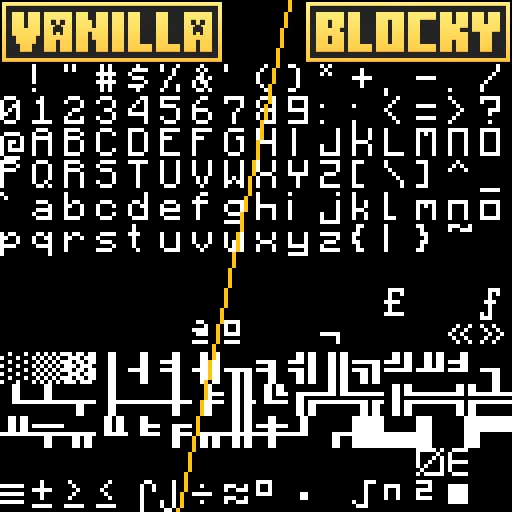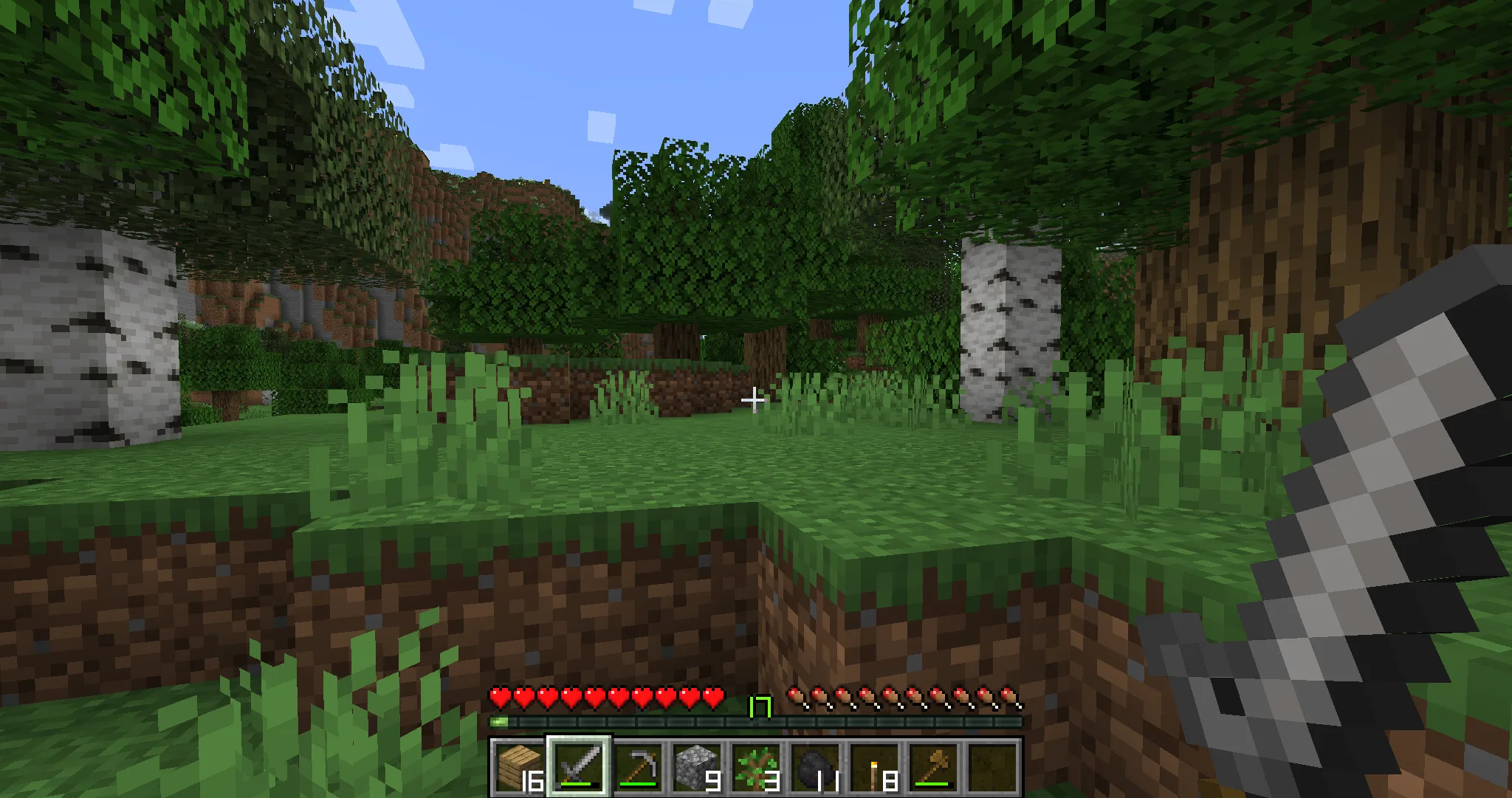
Blocky Font
Погрузитесь в Minecraft с новым шрифтовым пакетом, который придаёт игре уникальный блочный стиль. Простой и атмосферный, он идеально подходит для любителей минимализма.
Этот шрифтовой пакет предлагает простой и блочный дизайн, который добавляет игре уникальную атмосферу, напоминающую классические пиксельные стили. Он совместим с указанными версиями Minecraft и не требует значительных ресурсов, обеспечивая стабильную производительность.
Шрифт выполнен в минималистичном стиле, что делает текст чётким и легко читаемым, сохраняя при этом игровую эстетику. Он подходит для различных сценариев игры, от выживания до творческого режима, и не влияет на совместимость с другими ресурс-паками.
Особенностью пакета является его блочный дизайн, который может придать игре дополнительный шарм, особенно для поклонников ретро-стилей. Используйте его, чтобы освежить визуальный опыт в Minecraft без ущерба для производительности.